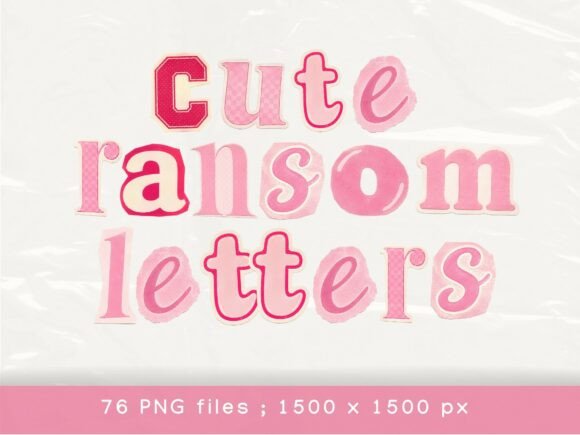
Ransom Letters, Pink Cutout Alphabet
หากคุณกำลังมองหาเนื้อหาคุณภาพสูงเช่น Ransom Letters, Pink Cutout Alphabet แพ็คเกจพรีเมียมนี้เป็นตัวเลือกที่ยอดเยี่ยมสำหรับโปรเจ็กต์สร้างสรรค์ของคุณ
สร้างขึ้นอย่างแม่นยำ Ransom Letters, Pink Cutout Alphabet ให้เวกเตอร์ที่สะอาด พิมพ์ตัวอักษรที่ราบรื่น และใบอนุญาตเชิงพาณิชย์เพื่อความสบายใจ
ไม่ว่าคุณจะสร้างผลิตภัณฑ์ POD (Print on Demand) คำเชิญงานแต่งงาน หรือกราฟิกโซเชียลมีเดีย Ransom Letters, Pink Cutout Alphabet ก็เหมาะสมอย่างยิ่ง